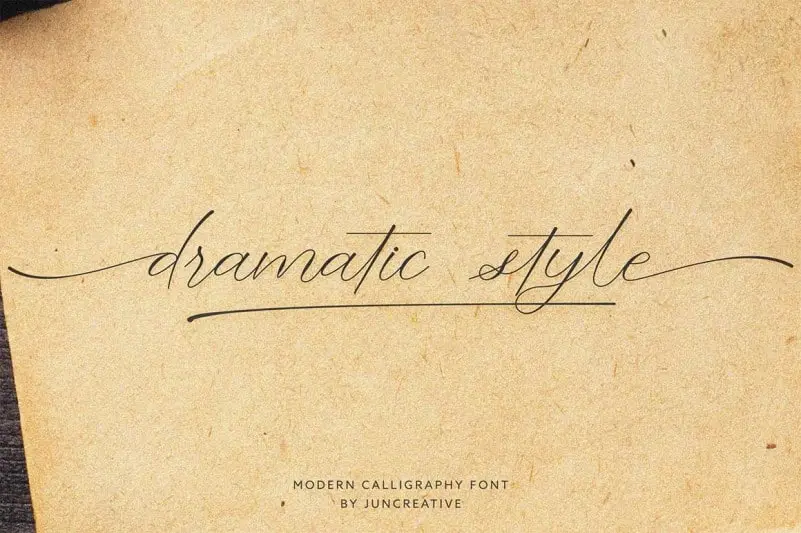
Dramatic Style Calligraphy Font – Download Grátis
Dramatic Style Calligraphy Font é uma fonte com traços suaves e elegantes que se destaca pela sua forma equilibrada e fluente. Esse tipo de letra, designado por JunCreative, combina perfeitamente com uma ampla variedade de projetos. Suas características bem balanceadas criam um visual agradável e confiante, ideal para adicionar à qualquer ideia mais criativa. Sua beleza faz dela uma fonte versátil que enriquece os seus trabalhos e as torna ainda mais vivas ao incorporar essa fonte em seu design. Explorando sua expressividade é possível notar como ela transforma o simples texto em um elemento visual impactante, capaz de destacar qualquer projeto.